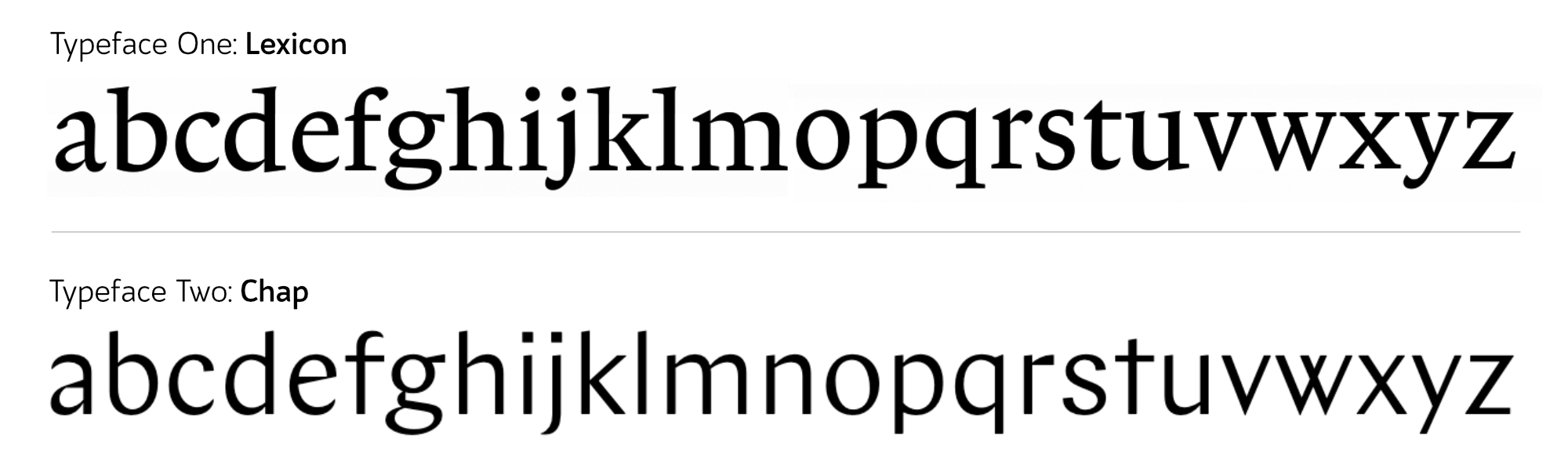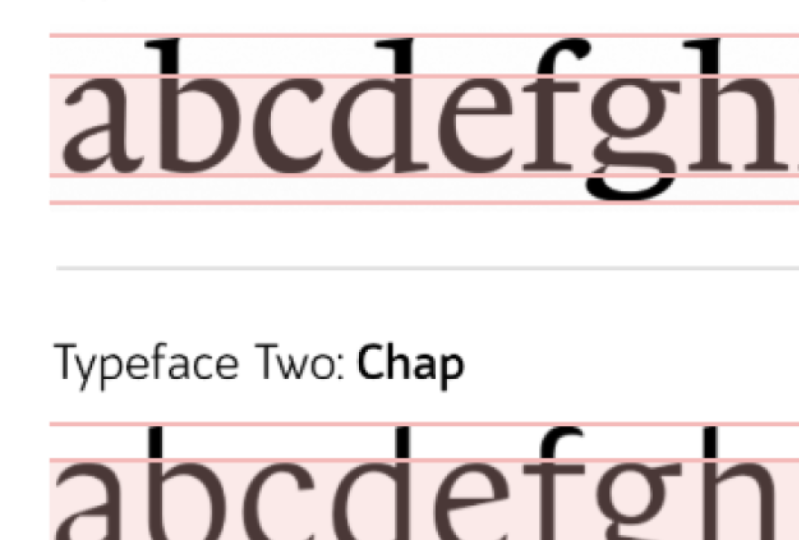
1. Einführung: In diesem kurzen Modul werden
wir uns mit der Typografie
für das UI-Design für unser Projekt
befassen . Diese Woche werden wir ein
paar Schriften beschreiben und darüber sprechen. Um dies zu tun, müssen wir die Anatomie der Schrift
kennen. Also werden wir über alle
Schriften sprechen
und wie man darüber
spricht, wie man sie nennt. Dann
schauen wir uns auch die Geschichte der Schriften an und wie verschiedene Schriften klassifiziert
wurden. Schließlich werden wir anfangen, uns zu
befassen, warum Sie sich für eine Schriftart und
nicht für eine andere
entscheiden könnten . Schriften machen fast
Ihr gesamtes Design , wenn Sie
ein UI-Design erstellen. Es ist also wirklich wichtig,
dass Sie wissen, wie man mit ihnen arbeitet. Und bevor Sie anfangen können, mit ihnen zu
arbeiten, müssen
Sie verstehen,
was sie sind. Sie müssen in der Lage sein, mit
Ihrem Kunden darüber zu
sprechen , und Sie müssen
wissen, was Sie gerade sehen. Beginnen wir also mit
dieser wichtigen Grundlage.
2. Typografie: Natürlich belegen Sie bereits einen
Online-Kurs in Web-Typografie. Ich werde dich nicht allzu sehr
darüber
belehren , wie wichtig
dieses Thema ist. Du weißt es schon
, deswegen bist du hier. vielen Jahren, Oliver, oder? Einstein machte den
sehr gültigen Punkt, dass das Internet zu 95% Typografie sei. Deshalb müssen wir wirklich, wirklich sicherstellen, dass
wir das richtig machen. In den Jahren seitdem ist
das Internet immer noch
sehr voller Typografie, und das meiste davon ist ziemlich schlecht. Gute Typografie hat
einige Auswirkungen auf die Effizienz und Effektivität
unseres Online-Lesens, wirkt
sich
aber auch emotional aus. Wenn wir nun gute,
abgerundete Designer sein wollen und
Designs kreieren möchten, die einen einzigartigen
Charakter haben , die die Markenbotschaft vermitteln. Aber wir möchten auch eine
Website erstellen, die minimal ist. Dann möchten wir versuchen,
all das andere Zeug in
der Topographie zu vermitteln ,
all das andere Zeug in ,
denn technisch gesehen könnten
wir eine Website
erstellen, auf der Sie einfach tippen,
vorausgesetzt, wir können Typografie
gut genug verwenden, um sie vorausgesetzt, wir können Typografie
gut genug verwenden zu vermitteln
diese Branding-Nachricht, um Charakter zu haben,
eindeutig zu sein und trotzdem lesbar zu sein. Dann ist das vielleicht alles was wir brauchen. Wir müssen es nicht
mit anderen Teilen des Designs übertreiben. Ich finde es endlos faszinierend darüber, wie die
Leute versuchen werden zu erraten, was es an Steve Jobs ist
, die ihn dazu
gebracht hat, solch
erfolgreiche Software zu entwickeln. Die Leute werden sagen, nun, Apple stellt Produkte her, die einfach einfacher zu verwenden
sind. Etwas, in dem ich persönlich keine Beweise
sehe. Die Leute sagen, nun, Apple-Produkte fühlen sich uns vertraut und
wohl. Sie sprechen mit uns auf eine Weise, wie wir verstehen, warum das zutrifft. Wir müssen dann noch einmal raten, wir müssen raten, oder
wie hat Apple das gemacht? Wie hat Steve Jobs das gemacht? Und vielleicht waren es
die Typenauswahl oder die Farben oder etwas, das
mit den Layouts der Seiten zu tun hatte. Dann müssen wir noch einmal raten, welche Fähigkeiten hat Steve Jobs entwickelt, um das so
gut zu machen? Nun, wenn wir
dem Erfolg von Steve Jobs nacheifern wollten, anstatt drei Vermutungen
hintereinander zu nehmen , um zu entscheiden, welche
Fähigkeiten wir erlernen sollten. Wir könnten uns einfach
seinen Lebenslauf oder seinen Lebenslauf ansehen. Und wir würden lernen
, dass er
Kalligraphie studiert hat, Schriften
studiert hat. Das war die Fähigkeit, die er
entwickelt hat, um so gut zu sein. Vielleicht ist
das Studium der Topographie besser darin die wichtigen Details
zu sehen
, die andere Menschen vermissen. Vielleicht gibt es uns ein besseres Verständnis dafür, wie man
Entwürfe als Ganzes anlegt. Vielleicht gibt es uns ein paar
technische Einblicke. Es ist wirklich alles Spekulation. Wenn wir versuchen wollten,
dem Gründer des
erfolgreichsten
Technologieunternehmens unserer Zeit nachzueifern dem Gründer des
erfolgreichsten . Vielleicht möchten wir wenigstens ein bisschen über Typografie
lernen. Es kann sich manchmal wie ein
winziges unbedeutendes Detail anfühlen, ob eine Schriftart mit einer anderen
funktioniert oder ob das
genau die richtige Größe ist. Aber diese winzigen Details summieren sich. Und Typografie ist das meiste von dem, was wir
auf einer Website
oder einer Webanwendung betrachten , diese
kleinen unbedeutenden, nervigen Details summieren sich und lassen uns unwohl fühlen
und sie machen uns nicht wie es zu benutzen und das Produkt sich wie harte Arbeit anfühlt. Typografie ist der
Ziegel und Mörtel der grundlegendste
Baustein einer Website. Und es macht etwa 95% aller Websites
und Anwendungen aus. Wenn Sie sich nicht sicher sind wie wichtig es ist, Topographie zu
studieren, sollten
Sie sich daran erinnern, dass der CEO
des erfolgreichsten
Technologieunternehmens unserer Zeit Typografie studiert hat.
3. Schriftart oder Schriftarten: In einigen
Phasen dieses Kurses werde
ich Ihnen einige
Terminologie geben, ein paar neue Worte. Ein Glossar, wenn du willst. Dies ist eines dieser Videos. Wir werden definieren,
was eine Schrift ist, was Topographie ist,
was eine Schriftart ist und was eine Glyphe ist. Jetzt ist eine Schrift
das Gesamtkunstwerk. Wenn Sie über Verdana aus der
Luft sprechen, Times New Roman,
sprechen Sie von einer Schrift. Eine Schriftart hingegen
ist eine Software, die Sie auf Ihrem
Computer
installieren, damit Sie die Schrift verwenden
können, wenn Sie beispielsweise eine Schrift in einer
Designsoftware auf Ihrem Computer
verwenden
möchten . Sie würden auf eine Website gehen, der die Schrift
verkauft wird, und Sie würden verschiedene Schriftdateien
von Matt-Websites
kaufen. Diese Schriftartdateien würden eine fett gedruckte Version
einer Schrift und eine kursive
Version der Schrift
enthalten . Und jeder wird in
einem Dateiformat wie einem Punkt T,
T F oder einem Punkt-ETF
oder einem Punkt mit OFF verfügbar sein T F oder einem Punkt-ETF . Diese Datei wird als Schrift bezeichnet. erinnern ist nicht allzu
wichtig, sich an den
Unterschied zwischen
diesen beiden Begriffen zu , denn selbst wenn
Sie in einem Designstudio arbeiten , rufen Sie oft
die Schriftart und verwenden vielleicht beide
Wörter austauschbar. Aber für den Rest dieses Kurses beziehe ich mich auf die
Schrift mit dem richtigen Begriff. Die Schrift ist das Bildmaterial, die Schriftart ist die Datei. Ähnlich wie ein
Lied ein
Musikstück ist und ein MP3 eine Datei ist. Jemand hört vielleicht
ein Musikstück und sagt, ich mag es wirklich,
dass dieser MP3 nicht völlig ungenau ist, aber es gibt wahrscheinlich einen besseren
Weg, dies auszudrücken. Man würde sagen, ich mag dieses Lied
wirklich. Topographie ist
möglicherweise zwei Dinge. Es wählt die Schrift aus. Und es ist auch, wie wir die Schrift,
die verschiedenen Größen, Linienhöhen,
Linienlängen
verwenden die verschiedenen Größen, Linienhöhen, , aber
auch wie und wann wir die fette Version
der Schrift verwenden, ist
Typografie die
Entscheidungen, die wir haben machen, wenn wir
die Schrift in
nicht allzu ferner Zukunft verwenden , werden
Sie ein typografisches System erarbeiten
. Das ist Topographie. Sie werden auswählen,
welche Schrift Sie verwenden, aber Sie
werden auch Entscheidungen
darüber treffen , wie sie verwendet wird. Während du
diese Entscheidungen triffst. Sie sind Typ- oder
Grafikdesigner oder Typograf. Und das letzte neue Stück Vokabeln, das ich
dir geben möchte, ist das Wort Glyphe. Eine Glyphe ist das einzelne
Symbol in einer Schriftdatei. Vielleicht möchten Sie dies als Buchstaben bezeichnen
, aber das ist nicht ganz
korrekt, da einige von ihnen Zahlen sind und einige von ihnen Grammatikpunkte
sind, und einige von ihnen sind
keines dieser Dinge. Glyph ist ein Begriff, den wir verwenden
, um sie alle zu erklären. Eine Glyphe ist das einzelne Symbol in der Schrift
in der Schriftdatei. Ob es sich um einen
Buchstaben, eine Zahl, ein Grammatiksymbol
oder irgendetwas anderes handelt. Eine Schrift ist das Kunstwerk. Verdana ist eine Schrift. Font ist die Datei
, die Sie auf
Ihrem Computer oder Ihrer Website installieren Ihrem Computer oder Ihrer Website ,
damit Sie
auf diese Schrift zugreifen können. Typografie ist die Kunst eine Schriftart zu
wählen und zu
entscheiden, wie sie verwendet wird. Und eine Glyphe ist das einzelne
Symbol in einer Schriftdatei.
4. Webtypografie: Bis vor kurzem wurden
Web-Typografie und gedruckte Topographie genau gleich
behandelt. Es gab eine Reihe von Büchern, eine Reihe von Tutorials. Jeder hat
eine Art von Typografie gelernt, aber die Web-Typografie unterscheidet
sich erheblich vom Drucken. Es gibt einige Einschränkungen bei
der Web-Typografie. Insbesondere wird jede
einzelne Schriftart, die Sie verwenden,
das Laden Ihrer Webseite verlangsamen. Sie sind darauf beschränkt, nur
Schriftarten zu verwenden , für die Sie
Weblizenzen haben, was teurer sein kann. Es gibt einige Dinge
, die bei der Web-Typografie einfach
anders sind , wir müssen
über die
Render-Engine des Browsers nachdenken und
wie sie
auf dem Bildschirm aussehen wird ,
anstatt darüber nachzudenken der Drucker oder die
Tinte, die wir verwenden. Und es gibt einige
Dinge, die mit Typografie
im Internet einfach
besser sind , die Leute haben die Möglichkeit auf
welcher Art von Bildschirm sie ihn lesen
werden. Sie können tatsächlich
die Größe des Typs steuern. Manchmal gibt es einige Regeln
, die einfach anders sind. Zum Beispiel können übergroße Texte, wie Sie auf einer Zeitschrift sehen,
doppelseitige Verbreitung. Auf
einem Mobiltelefonbildschirm wird es nicht funktionieren. Die Regeln dafür, wie dieser
Worker ganz anders ist, wenn der Text auf
dem Computer des Benutzers gerendert wird, wissen
wir nicht, ob etwas schief
gehen wird. Wir müssen also
im Rückfall programmieren und
darüber nachdenken, was passiert, wenn
eine Datei nicht geladen wird. Zum Beispiel könnte ein Benutzer
eine unglaublich schnelle
Internetverbindung haben . Ich werde
eine unglaublich langsame
Internetverbindung
in der Print-Welt haben . Das wäre so, als würden
sie es auf
ganz andere
Papierqualitäten drucken . Und natürlich
gibt es das Problem, dass jeder Benutzer möglicherweise einen anderen Browser
verwenden kann. Dies ist ein großes Problem für die
Typografie, da
die Browser zwar regelmäßig
aktualisieren und sie
mit vielen Rollen auf dem Laufenden bleiben. Manchmal mit
so etwas wie Topographie , die Dinge oft vergessen
und zurücklassen kann. Und manchmal können
Browser sehr, sehr langsam
neue Konventionen anpassen. Oder der Browser rendert
unseren Typ
nicht immer gut oder wie
die Regeln ihn sagen, er sollte sie rendern. Wir können einem
Computer nicht so vertrauen, wie wir unseren
Druckern auf unserem Papier vertrauen können. Und wahrscheinlich der größte, wesentlichste
Unterschied zwischen gedruckter Topographie
und Web-Typografie ist, wenn jemand
die typografischen Entscheidungen
für ein Stück Printdesign trifft, Sie erhalten oft
den genauen Text und dann liegt es an ihnen, ihn
zu stylen und
herauszufinden, wie er online auf die Seite
passt. Das ist nicht möglich. Zeitungen drucken möglicherweise
mehrere Artikel pro Tag. Normalerweise
arbeitet der Designer,
der Typograph, das System aus, bevor
der Artikel geschrieben wird. Als Typograf. Für die Web-Typografie ist
es Ihre Aufgabe,
ein typografisches System zu erstellen ,
anstatt vorhandene
Inhalte zu erstellen und zu erstellen.
Sie müssen ein
System erstellen, das für
etwas andere Szenarien gilt stellen Sie sicher, dass der Text
immer gut aussieht. Sieht es gut aus,
wenn die Überschrift
zehn Wörter lang ist und wenn sie zum Beispiel
ein Wort lang ist. Obwohl die absoluten Grundlagen
dafür, was die Topographie lesbar macht und was sie
gut aussehen lässt, in
Print und Web gleich sind. Es gibt viele, viele Dinge
, die ganz anders sind. Wir wollen Web-Typografie
als völlig
eigenständige Disziplin lernen . Einer der Hauptunterschiede besteht darin , dass die Topographie für das Web normalerweise entworfen
wird,
bevor wir
den Inhalt und nicht danach haben .
5. Nicht verbale Kommunikation: Wenn Sie jemals an
Verkaufsschulungen oder öffentlichen
Vorträgen jeglicher Art teilgenommen haben, haben
Sie den Kommentar wahrscheinlich
gehört. 93% der Kommunikation
sind nonverbal, obwohl das nicht gerade falsch ist, es ist eine übermäßige Vereinfachung. Es basiert auf einer Reihe von
Experimenten, die 1972 von einem Typen namens Albert Mehrabian
an der UCLA durchgeführt wurden. Mehrabian kategorisierte am
schlechtesten,
basierend darauf, wie negativ oder
positiv sie klingen. Zum Beispiel
ist das Wort Vergnügen wahrscheinlich
ein ziemlich positives Wort, während das Wort Tragödie ein ziemlich negatives Wort
ist. Mehrabisch kombiniert dann
die Wörter mit positiven oder negativen
Gesichtsausdrücken um zu sehen, wie sich die Menschen fühlen. Wenn sie zum Beispiel das Wort Tragödie hörte, aber als jemand einen ziemlich
positiven Gesichtsausdruck hatte, versuchte
Mehrabian dies auch, indem den Ton der Stimme
variierte. Zum Beispiel könnte jemand ein
ziemlich positives
Wort wie Vergnügen sagen , aber in einem negativen Tonfall. Danach betrachtete Mehrabian die Daten und kam zu dem Schluss, dass 55% unserer Kommunikation auf visuellen Informationen,
38% auf dem Ton der Stimme
und 7% auf dem tatsächlich angezeigten
Wort
beruhen 38% auf dem Ton der Stimme . Der Grund dafür, dass 93% der Kommunikation nonverbal sind, ist vielleicht
eine übermäßige Vereinfachung,
liegt darin, dass er nur getestet wie viel Emotionen
kommuniziert wurden und überhaupt nicht
wirklich Informationen . Er hat auch in
etwas getestet, das nicht wirklich ein reales Szenario ist. Und natürlich hat ein einziges
Wort, das aus dem Zusammenhang gerissen nicht
viel allein nicht
viel
Bedeutung. Wenn wir
mehrabischen Experimenten voll und ganz vertrauen, könnten
wir zu dem Schluss kommen, dass
die Art
und Weise, wie Sie es sagen,
wichtiger ist als das Wort, das Sie sagen. Aber wenn Sie einen ganzen Satz
oder tatsächlich einen ganzen
Absatz
sagen würden, ist wahrscheinlich wichtiger, welche
Wörter Sie wählen. Wenn wir uns jetzt unsere Websites
ansehen, ist
es wahrscheinlich ziemlich
unfair zu sagen, dass unsere typografischen Entscheidungen
wichtiger sind als die gewählten Wörter. Obwohl dieser Kommentar, 93% der Kommunikation nonverbal sind, ist eine massive,
massive Übervereinfachung. Es ist wichtig
, dass
wir uns daran erinnern , dass eine große
Menge an Kommunikation zumindest nonverbal ist zumindest nonverbal ist
und ein großer Teil dieser nonverbalen
Kommunikation emotional ist. Die Art und Weise, wie
die Menschen über das Unternehmen und die
Anwendung denken , die sie verwenden, wird weitgehend
durch
die typografischen Entscheidungen und
nicht durch die verwendeten Wörter kommuniziert . Wenn wir möchten, dass ein Leser
unserem Unternehmen vertraut und
eine emotionale Verbindung fühlt, ist
es wichtig, dass wir
gute typografische Entscheidungen treffen. Weitere Forschungen
fanden ähnliche Ergebnisse bei der Betrachtung des Gedächtnisses. Im Wesentlichen
erinnern sich die Leute
besser an die Bilder , als sie sich an
die eigentlichen Wörter erinnern. Wenn wir möchten, dass
sich die Leute daran erinnern, was wir geschrieben haben , wird
wieder die Art des Graphen, Auswahl ausgewählt wird, wirklich wichtig
sein. Einige Künstler, insbesondere abstrakte Künstler
wie Jackson Pollock, glauben,
dass Wörter eine ineffektive
Darstellung von Fehlern darstellen. Dass sie eine schwache Form der
Kommunikation sind ,
weil man sich auf die Bedeutung einer
endlichen Anzahl von Symbolen,
Wörtern und abstrakter Kunst
verlassen muss, um
auf einer tieferen Ebene authentischer zu kommunizieren. Denn sobald wir Wörter verwenden, werden
sie falsch interpretiert und
falsch dargestellt. Und deshalb
vertrauen wir ihnen etwas weniger mit etwas
wie Topographie indem wir
die Kraft dieser unbewussten oder unbewussten
Kommunikation nutzen. sich für Topographie
mit viel Charakter entscheidet, hat etwas unglaublich
Mutiges und Selbstbewusstes Eine Marke, die sich für Topographie
mit viel Charakter entscheidet, hat etwas unglaublich
Mutiges und Selbstbewusstes. Denn wie sehr sie es auch versuchen, sie
setzen unbewusst Teile ihrer Persönlichkeit
in diese Entscheidung ein. Und dieser kleine Teil
ihrer Persönlichkeit
kann keine Lüge sein. Während die Wörter, die sie
damit schreiben
möchten , ganz einfach Verbündet sein können. Aus diesem Grund
glaube ich fest an die Theorie , dass es in der
Fiktion mehr Wahrheit gibt als in Sachbücher. Wenn jemand eine
Autobiografie schreibt, dann versucht
man natürlich irgendwie von etwas in seinem Leben zu überzeugen . Aber wenn jemand Fiktion schreibt, gießen
sie versehentlich seine wahre Persönlichkeit
in das Buch ein. Ich denke, wir können durch das
Lesen von Fiktion weit mehr
über die menschliche Rasse lernen als durch das
Lesen von Büchern über Anthropologie. Ebenso denke ich, dass Sie
durch ihre typografischen Entscheidungen
genauso viel von einer Marke lernen können durch ihre typografischen Entscheidungen
genauso viel von als die Wörter, die sie
darin schreiben. Es wäre absurd
von uns zu vermuten , dass 93% der Kommunikation nonverbal sind oder sogar darauf hinweisen, dass die Topographie
wichtiger ist als die gewählten Wörter, es sei denn,
wir haben eine Bewerbung mit nur einem einzigen
Wort in der Anwendung. Allerdings die nonverbale
Kommunikation, Dinge wie Topographie oder Kommunikation auf einer
ganz anderen Ebene. Sie kommunizieren
auf emotionaler Ebene. Und das ist sehr wichtig für
unsere Bewerbung. Wenn aus keinem anderen Grund, weil wir Nachrichten vertrauen auf
emotionaler Ebene
kommuniziert werden.
6. Anatomie des Typs: Verbesserung unseres Wortschatzes
über Schriften. wird uns nicht nur besser
machen mit der Schrift zu arbeiten, es wird uns auch
besser machen, mit unserem Team zu kommunizieren oder
mit unseren Kunden zu kommunizieren. Aus diesem Grund ist es
wichtig, dass wir uns etwas Zeit nehmen, um alle Namen der
Anatomie der Typografie zu lernen. Das erste, worüber man sprechen muss,
ist, wie wir die Höhe definieren. Es gibt die Gesamthöhen
der Glyphen in der Schrift, aber es gibt auch die Kappenhöhe, und so hoch sind die
Großbuchstaben. Dann haben wir die x-Höhe. Dies ist die Höhe
eines Kleinbuchstabens. Nicht unbedingt die genaue
Höhe eines Kleinbuchstabens x, da manchmal
verschiedene stilisierte Xs möglicherweise nicht genau mit der x-Höhe
übereinstimmen. Wir denken besser daran die x-Höhe die Höhe
der Kleinbuchstaben ist. Und wenn wir über
die Höhe der
Kleinbuchstaben sprechen , schließt
dies nicht die
Aufstiege und Abstiege ein. Dies sind die Bits, die Sie
sich vorstellen können, wenn sie unter oder über der Linie liegen. Ein Kleinbuchstaben H
hat beispielsweise einen Ascender, der über der x-Höhe
des Kleinbuchstabens liegt. Und ein Kleinbuchstaben g
hat einen
Abstreißer ,
der unter den Kleinbuchstaben fällt. Wir beziehen uns auf die Zeile, der der Buchstabe der Strich
war. Wir könnten also über
die Strichbreite sprechen und darüber
sprechen, wie
breit die Linie ist. Die vertikale Hauptlinie wie bei einem Großbuchstaben T wird
als Stamm bezeichnet. Alle horizontalen Linien wie
die in der Mitte eines Großbuchstabens a werden als Querlatte
bezeichnet. Alle Buchstaben, bei denen der
Hauptstrich gekrümmt
ist, wird manchmal als Wirbelsäule bezeichnet , zum Beispiel hat
Großbuchstaben S eine Wirbelsäule. Die abgerundeten Bereiche wie auf einem O oder einem
heißen Schüssel. Der geschlossene Bereich in der
Schüssel wird als Zähler bezeichnet. Und wenn dieser Bereich wie ein E oder C
geöffnet ist, nennen
wir ihn einen offenen Zähler. Manchmal
hat ich die Schrift diese kleinen Füße, diese Hüte, wir nennen sie Serifen. Und wenn es keine Serif hat, bezeichnen
wir das Ende
des Briefes als Terminal. Immer wenn die Serifen herausragen die
Breite des Buchstabens
leicht erhöhen, würden
wir dies als Überschwingen bezeichnen. Und alle diagonalen Linien, wenn wir eine diagonale Linie
haben die vom Buchstaben aufragt, nennen
wir ihn einen Arm, und eine, die von einem Buchstaben
zurückbleibt, nennen
wir es eine Verzögerung. Lasst uns ein M und N oder ein H mögen,
haben, was wir eine Schulter nennen, einen abgerundeten oberen rechten
Teil des Buchstabens. Und ein Brief wie eine Warteschlange
hat einen Schwanz, der herausragt. Manchmal kann die Schrift
einige kleine dekorative
Linien hinzufügen , die nicht erforderlich sind, um den Buchstaben zu
identifizieren. Wir könnten das einen Schwamm nennen. Diese neuen Begriffe und
unser Vokabular haben , um
über unsere Schriften zu sprechen. Es wird es uns viel
einfacher machen,
Entscheidungen zu treffen und
Gespräche zu führen. Zum Beispiel könnten wir
sagen, dass Helvetica mit einer großen X-Höhe es
bei geringer Größe lesbar machen
könnte. Dies reduziert jedoch die Höhen
des Aufstiegs in Kleinbuchstaben h. So sehen Kleinbuchstaben h und Kleinbuchstaben n
viel ähnlicher aus. Wir könnten sagen, dass Futura
zwar
sehr einfache geometrische Formen verwendet ,
die ein O,
ein E, a, C und ein ähnlich machen könnten . Es ist auch erwähnenswert, dass das SEA einen sehr
großen Zähler hat, es deutlich
anders aussieht als diese
anderen Buchstaben. Eine serifenlose Schrift hat keine Serifen und
hat daher keine Überschüsse. Wir können eine
verdichtetere Version haben, die sie
innerhalb von Schaltflächen oder Menüs
viel geeigneter macht . Es gibt drei Beispiele für
Gespräche, die Sie jetzt führen können, sei es in Ihrem eigenen Kopf mit Ihren Kunden oder
mit Ihren Teamkollegen über Schriften, die Sie wahrscheinlich vor fünf Minuten
hätten führen können. Werfen Sie einen Blick auf ein paar
Schriften um Sie herum und identifizieren Sie die unterschiedliche Anatomie in jedem Buchstaben in der Schrift. Und sehen Sie, was die Vor- und Nachteile dieser Merkmale für jede Schriftart sind. lernen,
über die Anatomie von
Schriften zu kommunizieren , wird es Ihnen viel einfacher
machen, Entscheidungen zu treffen, insbesondere mit einem Team. Verbringen Sie einige Zeit damit,
sich mit diesen Worten vertraut zu machen. Jedes winzige Detail eines Briefes hat einen eindeutigen Namen. Oft verwenden Leute, die
Schriften entworfen haben, diese
Namen ziemlich oft. Als Typograf
oder Webdesigner Sie sie wahrscheinlich
nicht zu viel verwenden,
aber es lohnt sich, ein wenig
Zeit damit zu
verbringen , diese zu lernen. Insgesamt interessieren wir uns
wahrscheinlich mehr für die Eigenschaften der
Schrift, die Gesamtform,
wie breit sie sind, wie dick der Strich ist,
was der Kontrast und die
Dicke des Strichs ist, ob es Serifen hat oder nicht. Aber irgendwann wirst
du all diese Wörter benutzen. Also stell sicher, dass du sie kennst.
7. Druckpresse: Im 15. Jahrhundert schuf
ein deutscher Mann namens
Johannes Gutenberg beweglichen Typ oder
die Druckmaschine oder so zumindest
die europäische Geschichte. Die Druckmaschine wurde natürlich viel früher in China
erfunden. Das Problem in China
ist, dass es einfach
viel zu viele Charaktere
sind , um nützlich zu sein. Es ist teuer, eine Druckmaschine zu
erstellen, aber es ist auch sehr zeitaufwendig, alle Buchstaben
anzuordnen. Und noch wichtiger ist, dass
es viel schwieriger wird, die
Größe der Buchstaben zu reduzieren. In Europa sahen die
meisten Bücher um
Gutenbergs Zeit so aus, ein Textstil, den wir heute als
schwarzer Brief bezeichnen. Und man würde sehr,
sehr selten sehen jemand dies mehr benutzt, abgesehen von Nazi-Deutschland
, abgesehen von Nazi-Deutschland
, das es als eine Art
Ablehnung von etwas Neuem oder Modernem nutzte, weil sie
gegen globalisierte Ideen waren. Und manchmal Tattoo-Studios. Möglicherweise weil der schwarze Buchstabe ziemlich dekorativ
aussieht oder Sie einen
ganzen Rücken haben und Sie nur
sechs Buchstaben darauf legen möchten. Aber wenn Sie versuchen, eine ganze Seite eines Buches zu
drucken, ist
dies eigentlich kein
besonders nützlicher Typ. Es ist etwas zu dekorativ,
um zwei kleine zu machen, aber es hat auch diese sehr
dicken, rauen schwarzen Linien , die bedeuten, dass Sie, wenn
Sie sie
kleiner machen und mehr
Buchstaben zusammenstopfen, einen sehr dichten
Bereich von Kontrast auf der Seite, die
nicht zu
einem Leser einlädt oder leicht zu lesen ist . Die Druckerei
hätte wahrscheinlich nicht
viel genutzt, wenn Nicholas Jensen nicht
gewesen wäre. Und Nicholas Jensen wäre nicht sehr nützlich
gewesen, wenn es nicht den humanistischen
winzigen Kalligraphie-Stil aus Verona im 15. Jahrhundert in der
Renaissance gegeben hätte Italien, in dem sie sich auf
Black Letter Letter
Letter Moderna. Mein Latein ist nicht perfekt, aber das bedeutet moderne Buchstaben. Und sie werden auf das bezeichnet,
was die Römer früher als Letzten Tag und TK
verwendeten. Die Römer hatten gerade
die Großbuchstaben. Sie haben also viel
experimentiert, um zu entscheiden, wie
Kleinbuchstaben aussehen, und als Ergebnis haben sie
etwas geschaffen, das
weitaus moderner aussah als schwarze Buchstaben. Jensen verbrachte einige
Zeit damit, diese neuen
Renaissance-Briefe und einige
der Entscheidungen zu beobachten und mit ihnen zu
experimentieren , die
er bereits
im 15. Jahrhundert
bis heute getroffen die
er bereits
im 15. Jahrhundert
bis heute hat, darüber, wie entscheiden, wie ein Ende
aussieht oder ein D aussieht. Jensen hat eine Schrift erstellt,
die viel,
viel kleiner als der
schwarze Buchstabentyp geschnitten werden kann und daher viel
wirtschaftlicher ist, um
viel mehr Buchstaben auf
einer Seite zu passen viel mehr Buchstaben auf und daher
mehr Informationen. Es kann
viel billiger
und effizienter in ganz Europa verteilt werden . Sie können heute noch eine Form von
Jensens Schrift verwenden. Sie könnten zum Beispiel von Adobe Jensen diese
Schrift hier finden. Wenn ja, fragen Sie sich
vielleicht warum bezahle ich für etwas , das ungefähr 500 Jahre
alt ist und nicht urheberrechtlich geschützt ist? Nun, tatsächlich ist der Aufwand, den
Adobe unternommen hat,
um diese Schrift
neu zu erstellen viel mehr, als
Sie denken würden. Sie sehen, wenn Sie
ein altes gedrucktes
Buch in Jensen nehmen , eigentlich nicht jedes E dasselbe. Es gibt winzige Diskrepanzen in den verschiedenen Kürzungen
des Briefes. Damit Adobe
einen einzelnen Buchstaben erstellen kann, müssen
sie Hunderte von
Jensen 0s scannen und dann
ungefähr herausfinden, wie hoch der Durchschnitt ist. Es gibt mehrere Gründe, warum
jedes E auf der Seite nicht
identisch war , während sie nicht unbedingt alle Schnitte
genau gleich waren. Und einer dieser Gründe ist
tatsächlich, dass die Leute es
gewohnt waren ,
handgeschriebene Seiten zu lesen , dass die gemeinsame Monotonie
, eine Seite mit
einheitlichen identischen Symbolen zu sehen , das Gehirn der Menschen in den Schlaf bringen würde . Sie konnten sich nicht mit diesem Material beschäftigen oder mit diesem Material
interagieren. Je weniger neuartig
der Abdruck jedes Wortes auf der Seite ist, desto weniger neuartig der
Abdruck und unser Gehirn, desto unwahrscheinlicher
ist es, dass
wir uns daran erinnern und uns mit dem Material beschäftigen. Es lässt uns auch
verschiedene Größen etwas
anders
gefangen haben , denn wenn die Art und Weise, wie diese Wahrnehmung funktioniert, sehen
wir kein großes E und ein kleines E derselben
Schrift identisch war. Sie erscheinen tatsächlich etwas anders, wenn
sie kleiner sind. Etwas, das wir
optisches Warten nennen. Realistisch gesehen müssen Sie, wenn Sie heute eine Schrift
wie Jensen
neu erstellen möchten, heute eine Schrift
wie Jensen
neu erstellen möchten,
mehrere Schriftdateien neu erstellen, eine für Texte mit einer Höhe von 16 Pixel und dann eine völlig
separate Schriftdatei für Texte, die
20 Pixel hoch sind. Zum Beispiel bei einem
etwas anderen Schnitt ein etwas anderes
optisches Gewicht. Weil eine Schrift 20 Pixeln nicht wie
eine etwas größere Version
einer Schrift aussieht eine etwas größere Version
einer , die mit 16 Pixeln angezeigt wird. So funktioniert die Wahrnehmung nicht. Wir werden später mehr
darüber sprechen, aber das ist die Schrift Jensen, und das
nennen wir jetzt eine alte Serife. Sie würden Jensen wahrscheinlich nicht
wirklich verwenden weil es zu viele
Auswirkungen der Zeit hat,
es sei denn, Sie
wollten ein Design erstellen , das anscheinend ein
15. Jahrhundert nicht dazu bringt. Sie würden wahrscheinlich etwas
mehr wie Garamond wählen, wenn Sie eine
Serifenschrift im alten Stil wünschen. Die Erfindung
der Druckmaschine brachte eine ganz neue Herausforderung mit sich. Wie können wir
die Größe der Buchstaben reduzieren und trotzdem lesbar machen und trotzdem bequem und
angenehm zu lesen machen. Glücklicherweise wurde dies
bereits von
Kalligraphen in Italien
ungefähr zur gleichen Zeit gelöst . Und so entstanden Schriften wie Jensen
oder Garamond, die sehr komfortabel
und leicht zu lesen sind. Schon kleinste 16
Pixel hoch auf unserer Seite, der Druckertafel. Andere Herausforderungen, darunter,
wie eintönig es aussah, eine Seite
mit identischen Symbolen zu sehen, und auch wie das
optische Warten für größere
und kleinere Zeichen
unterschiedlich ist . Dies sind Probleme
, die wir damals gelöst haben und
die wir
seitdem vergessen haben. In der Tat sagen viele Leute
, dass Typografen oder die letzten 200 Jahre
faul geworden sind.
8. Serif Typeface: Wir können
Serifenschriftarten in ein paar Kategorien einordnen. Zuallererst haben wir
für alte Serifen wie Jensen oder Garamond, über die
wir gerade gesprochen haben. Darauf folgt haben wir Übergangsserifen
wie Baskerville , über die wir in Kürze sprechen werden. Und dann haben wir moderne Serifen
wie Bodoni und Diderot. Je moderner die Schrift, desto mehr Kontrast
zwischen den Linienbreiten, desto alter Stil oder
traditioneller, desto humanistischer, desto mehr scheint sich
die Linienbreite
ineinander zu verschmelzen , als wäre sie
von Hand gezeichnet mit einem Stift. Betrachten wir zunächst
diese Übergangsschriften
wie Baskerville. Jetzt lebte John Baskerville
in Birmingham, England, und gegen Ende seines Lebens beschloss
er, sein
gesamtes Geld
in den Versuch zu investieren , die
Druckprozesse zu verbessern. Also versuchte er, die Tinte und
das Papier zu
verbessern , um einen
konsistenten Blick auf die Seite zu bekommen. Und tatsächlich, als er
das Druckpapier und die Tinte fast
wie eine Vitrine verbesserte , schuf
er diese
Schriftart, Baskerville, die
sehr dünne Linien und
ziemlich dicke Linien auf demselben
Papier haben und aussehen könnte ziemlich gut. Es war möglicherweise nicht möglich, mit Baskerville zu drucken, bis die Qualität der Tinte und des
Papiers so verbessert hatte , dass dies auf der Seite knackig
und sauber aussehen würde, die Leute hassten
Basketbällchen-Schrift an der Zeit sagten
die Leute, es sei
ziemlich schwierig , diese sehr dünnen Linien zu sehen. Sie sagten, es schadet
ihren Augen sogar. Wahrscheinlich waren viele Druckmaschinen
wahrscheinlich irgendwie eifersüchtig. Und seien wir ehrlich,
seine Bücher kosteten einfach mehr, weil sie mit
hochwertigerer Tinte und Papier bedruckt
wurden . Basketball ist Metallschrift
Symptom meist verschwinden, aber es tauchte
kurz vor der
Französischen Revolution in Frankreich auf, als es für das Material für
einige revolutionäre
Ideen verwendet
wurde , die gedruckt wurden. Die Tatsache, dass es anders,
frisch und modern
aussah ,
machte es perfekt, um diese
revolutionären Ideen
auszudrücken. Und nicht lange danach kreiert es
ein anderer französischer
Designer,
hat es diese Schrift gemacht, die
fast gleichbedeutend mit der Französischen Revolution und mit
viel modernistischen Ideen ist, einem Italiener
sehr ähnlich ist
Schrift namens Bodoni. Ist ein Bodoni beide
gleichermaßen beliebt? Wenn wir über
moderne Serifenschriften nachdenken, wenn wir die drei
nebeneinander stellen, können
wir sehen, wie die drei
Stufen der Serifenschriften
zunehmend weniger
humanistisch und
kontrastreicher werden, wenn zunehmend weniger
humanistisch und die Menschen es bekommen gewohnt,
Dinge zu betrachten, die nicht von Hand
geschrieben sind und sich daran gewöhnt haben, die
verschiedenen Kontraste zu identifizieren wenn ich einen kleinen
Typ auf einer Seite betrachte, habe ich kürzlich gehört, dass jemand
auf den Unterschied in Bezug auf Stil war wie der Unterschied im Stil
der Renaissance, des Felsens und der
Erleuchtungsfehler. Es gibt eine letzte Stufe
der Serifen-Typografie,
nämlich die ägyptische Serif, die
manchmal als Serifenplatte bezeichnet wird , wie zum Beispiel Rockwell. Dies wurde irgendwann
in der viktorianischen Ära populär als wir wollten, dass unsere
Plakate
schöne, große, druckvolle Überschriften haben . Und
oben auf unserem Poster sah es sehr mutig und selbstbewusst aus. Im 21. Jahrhundert passen
neue Schriften sehr selten bequem in
eine Kategorisierung. Zum Beispiel ist die Schriftart, die ich
während dieses Kurses für Überschriften
verwendet habe , bei ein paar anderen
Kursen diese , die
eine Keilserif ist. Es passt in keine
dieser anderen Kategorien, die diese großen dreieckigen Serifen haben, was meiner Meinung nach ultramodern
aussieht. Traditionell passen wir
Serifenschriftarten in drei Kategorien alter Stil,
Übergangs-und Modern. Sie können sich vorstellen, dass
diese wie Garamond, Baskerville
und Bodoni sind, wobei jede Generation
etwas weniger
humanistisch wird und
einen etwas dickeren
Kontrast mit
Serifs aus hat einen etwas dickeren
Kontrast mit eine dieser
drei Perioden in der Geschichte. Es gibt ihm einen unverwechselbaren
Charakter aus dieser Ära. Heute gibt es alle
Arten von neuen Arten von Serifen wie Slab Serif
und Keilserif, aber nicht bequem
in eine
dieser Kategorien passen .
9. Sans Serif Typeface: Zu Beginn
des 20. Jahrhunderts
wollten
Avantgarde-Künstler
alles, was
zuvor gekommen war, ablehnen und neue,
einfachere Designs für alles kreieren . Puristen wollten nichts
auf einem Buchstabenformular, das von dem
grundlegendsten reinsten Symbol darunter
ablenkte. Natürlich begannen die Designer, die Serifen
zu entfernen. Jetzt wissen wir, dass
diese kleinen Serifen uns
wahrscheinlich helfen,
einen Buchstaben von einem anderen zu erkennen. Aber sie sehen auch
insgesamt
etwas unordentlicher,
etwas komplexer aus. Und 1927 gründete Paul
Renner Futura. Diese Schrift, die
ausschließlich aus geometrischen Formen
besteht, machte es
für uns unglaublich schnell, sie wahrzunehmen und in unser Gehirn
zu bringen. Und wenn nichts
anderes,
passt es perfekt zum Stil der Zeit. Wenn es nicht die
Tatsache gab, dass er kurz darauf 1927 in
Deutschland lebte , übernahmen
die Nazis die
Kontrolle über Deutschland. Und wie wir bereits darüber gesprochen haben, liebten
sie schwarze Briefe,
sie liebten altmodisch. Sie wollten nichts
Neues oder Modernes Aussehen. Futura wurde tatsächlich populär oder rund um den Rest
der Welt und wurde
nach dem Zweiten Weltkrieg zu einer internationalen Schrift , Helvetica wurde
in der Schweiz gegründet, und dies ist jetzt
die beliebteste, am häufigsten verwendete Schrift der Welt. Es sieht gut aus, so
groß du willst, und es kann ziemlich klein gelesen werden. Es ist sehr minimalistisch, hat aber immer noch ein
bisschen Charakter. Und der Charakter war genau das, was Eric Gill
dazu motivierte, Gill Sans zu erschaffen. Jetzt hat dies alle Vorteile
einer serifenlosen Schrift, aber sie hat ein leichtes
humanistisches Gefühl. Diese serifenlosen Schriften waren alle ein riesiger Hit auf der Welt , die nach
dem Zweiten Weltkrieg entstanden sind. Eine Welt, die
nach Veränderungen hungrig war und die Globalisierung
der Welt
akzeptieren wollte . Und dann haben wir Computer erfunden, Computer mit sehr
niedriger Auflösung für einen pixeligen Bildschirm. Und so wurden Sans
Serifs natürlich noch
beliebter, weil
sie auf diesen Monitoren von schlechter
Qualität leicht zu
rendern waren . Schriften wie Vedanta wurden eine Art
Helvetica für
den Computer
erstellt , bei dem jedes
Pixel in Betracht gezogen wurde, um sicherzustellen, dass es gut aussah, wenn es auf einem pixeligen
Computerbildschirm
gerendert wurde. Später wurde Arial auch aus dem gleichen Grund
geschaffen, nachdem er jahrzehntelang
auf Bildschirme mit
Text in Verdana gestarrt hatte und jetzt
ziemlich veraltet aussieht. Wenn Sie heute eine Website gesehen haben und alle Texte in Verdana
geschrieben wurden, denken
Sie vielleicht, dass Sie nur
30 Jahre zurückgereist sind,
die Tage, in denen Sie
eine Schrift als
moderner betrachten , nur weil sie keine
Sans ist Serifen sind längst verschwunden. Tatsächlich könnten sie irgendwie veraltet
aussehen, weil alles, was
auf einem Bildschirm und serifenlos gerendert
wird, so aussieht, wie Sie es in den 1990er Jahren
angeschaut haben. Genau wie
verschiedene Serifenschriften uns
an Perioden erinnern in der Geschichte. Die meisten serifenlosen Schriften erinnerten uns
auch daran was heute wirklich
eine historische Periode ist. Und natürlich werden ständig neue
Klassifizierungen und neue Schriften
erstellt. Die Schrift Gotham wurde rund um das
Jahr zweitausend
geschaffen und die USA wurden wegen
Obamas politischer Kampagne populär gemacht . Die Verwendung einer brandneuen,
hochmodernen Schrift macht genauso eine politische Aussage
wie die Verwendung einer alten. Nazi-Deutschland mit
altmodischen schwarzen Buchstaben gab eine politische
Aussage über traditionelle Werte ab und was sie wichtig
hielten,
genauso wie die Französische Revolution gab eine politische
Aussage über
traditionelle Werte ab und was sie für wichtig
hielten,
genauso wie die Französische Revolution
Baskerville
und dann abziehen, wir eine Erklärung darüber ab,
wie vorausschauend sie waren und wie sie Teil einer neuen Welt sein wollten
. Gotham passte perfekt zu Barack Obamas
politischer Kampagne. Barack Obama
versuchte,
als etwas Neues und Anderes angesehen zu werden . Er schien keine neue Wahl zu sein , weil
er eine Serifenlose benutzte. Er schien eine neue Wahl zu sein
, weil er Gotham benutzte. Seine Plakate
hätten diese Art von Auswirkungen nicht gehabt, wenn sie in
Helvetica oder Gill Sans geschrieben worden wären. Die Relevanz von
Schriftklassifizierungen ist
bei neuen Schriften viel weniger wichtig. Tatsächlich
teilen sich
Typografie-Designer oft auf verschiedene
Klassifizierungen oder erstellen neue. Es gibt keine Klassifizierung
, die zu unserer modernen Zeit passt. So wie sich die Mode in anderen
Branchen unglaublich verschärft hat , hat
sich auch die
Mode in Schriften erhöht. Designer begannen Anfang des 20. Jahrhunderts mit
der Erstellung
serifenloser Schriften . Und sie wurden nach dem
Zweiten Weltkrieg wirklich populär, als sich die
Menschen
auf eine neue internationale,
globalisierte Welt freuten,
serifenlose Schriften wurden nicht unbedingt beliebter weil sie
leichter zu lesen waren. Wir könnten wahrscheinlich sagen, dass es einfacher ist,
sie wahrzunehmen , sie
in unser Gehirn aufzunehmen, aber wahrscheinlich ein bisschen schwer zwischen ihnen zu unterscheiden
oder die Buchstaben zu erkennen. Sie wurden aber auch
beliebter, weil sie auf
minderwertigen Computermonitoren
einfacher zu rendern waren . Heute
sehen
einige serifenlose Schriften wahrscheinlich genauso veraltet aus wie
Garamond Vedanta, ist jetzt ein Stück Geschichte, da neue Schriften
entworfen und erstellt werden, sie überschreiten oft
Genres oder -Klassifizierungen.
10. Zusammenfassung: Typografie ist die Stimme
unserer Markenanwendung
oder eines Dienstes. Einige Stimmen sind klarer, aber die klarste Stimme ist
möglicherweise nicht die engagierteste oder
denkwürdigste. Brauchst du eine Stimme
mit mehr Charakter? Und wenn ja, welcher Charakter? Jede Schrift, wie jede
Stimme, hat eine Persönlichkeit. Welche Schriftart wir auch wählen, sie wird
etwas ausdrücken, das wir brauchen, um sicherzustellen, dass es
das Richtige ausdrückt. Eine Schrift spricht aus
einer Zeit und einem Ort. Wir müssen den richtigen auswählen. Und wenn wir uns mehr in Richtung
eines vollständigen typografischen Systems bewegen , müssen
wir möglicherweise
mehrere Schriften verwenden, und sie müssen gut funktionieren und sich gegenseitig
ergänzen.